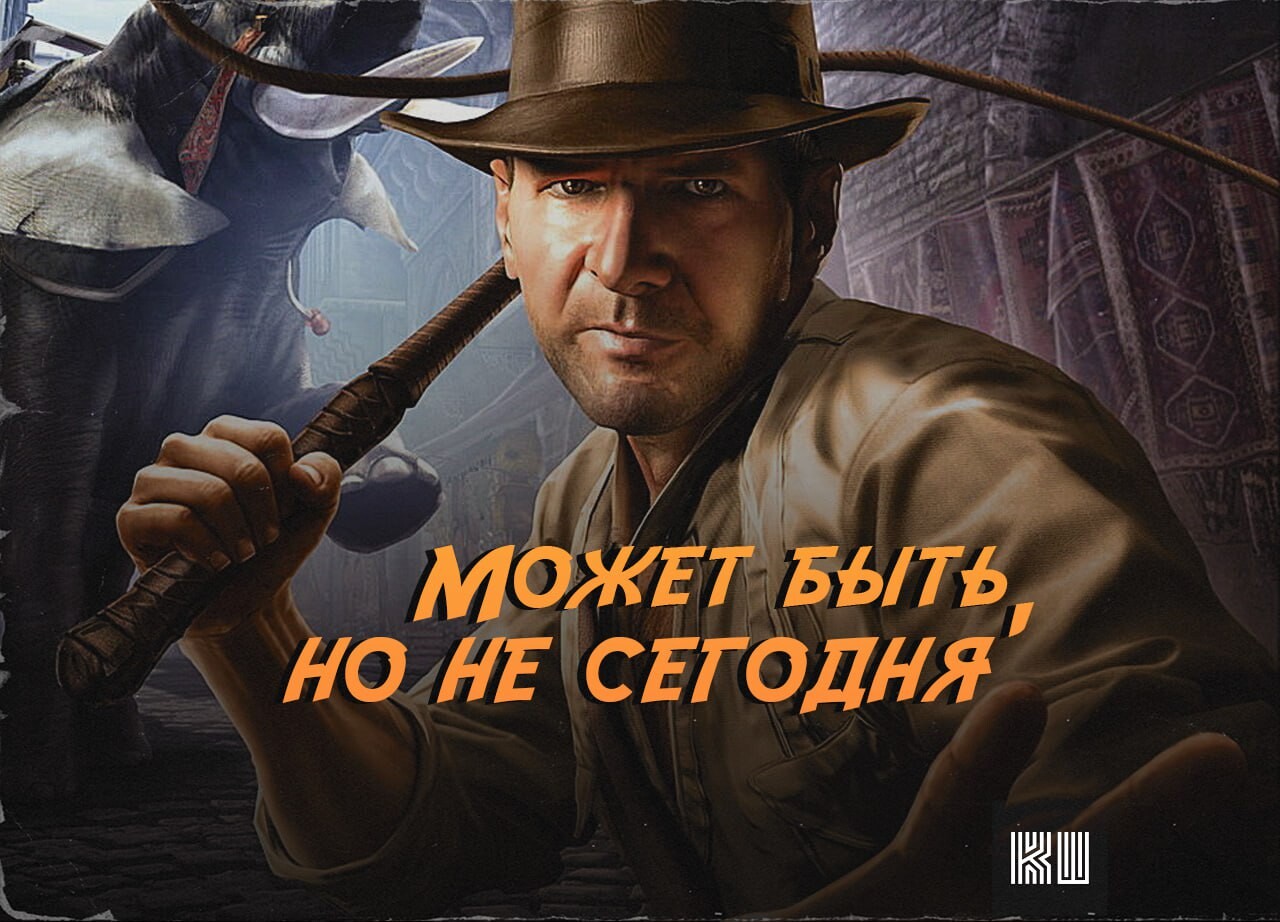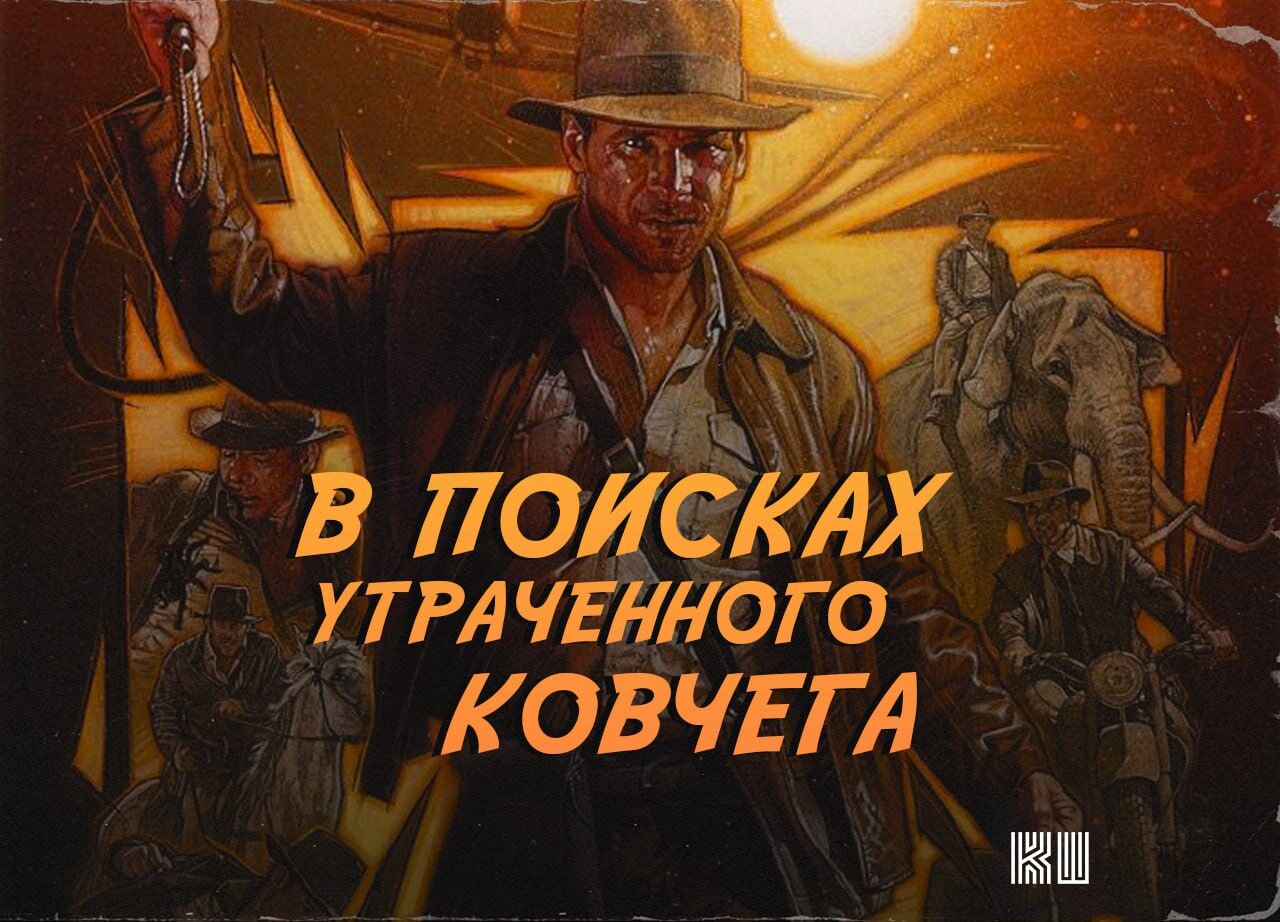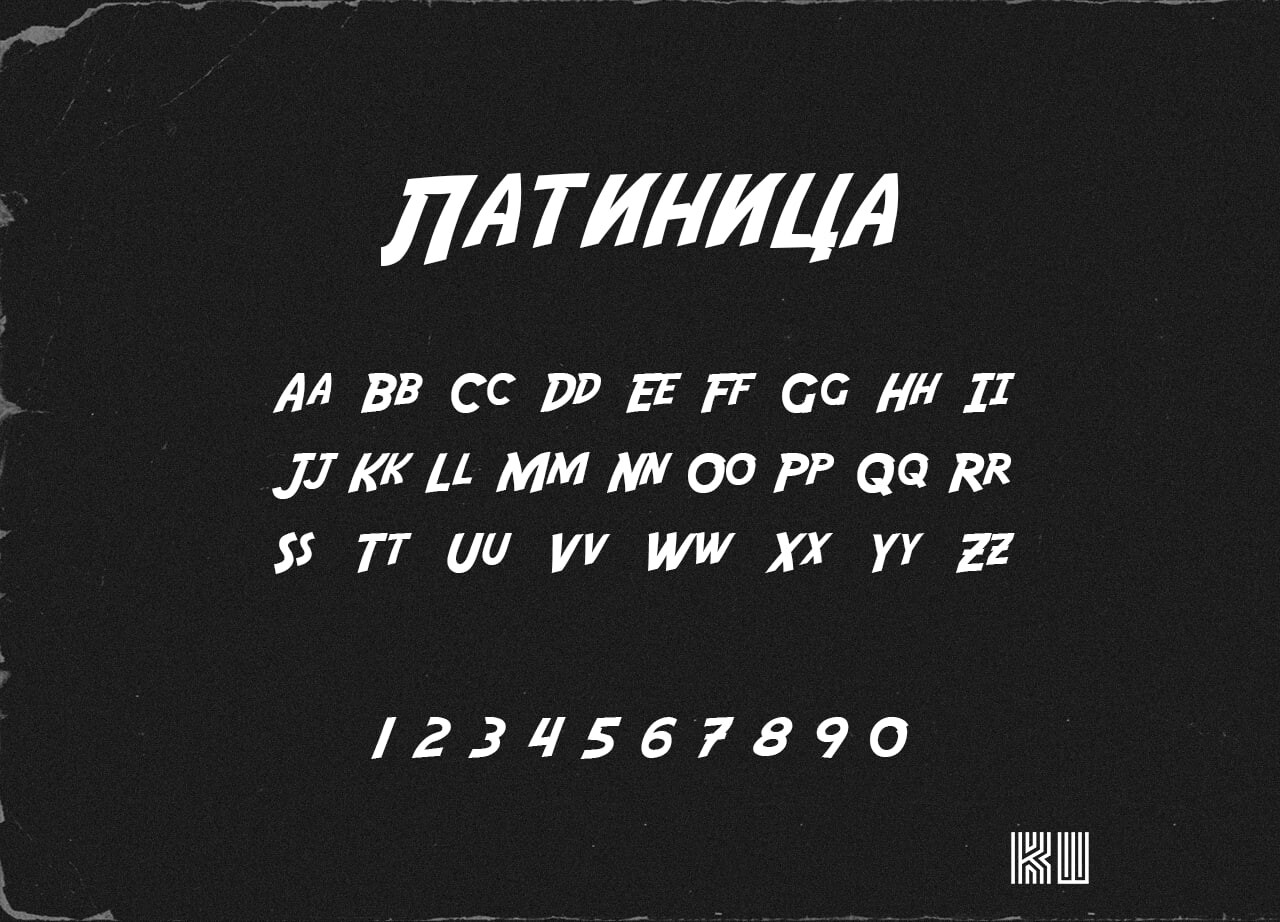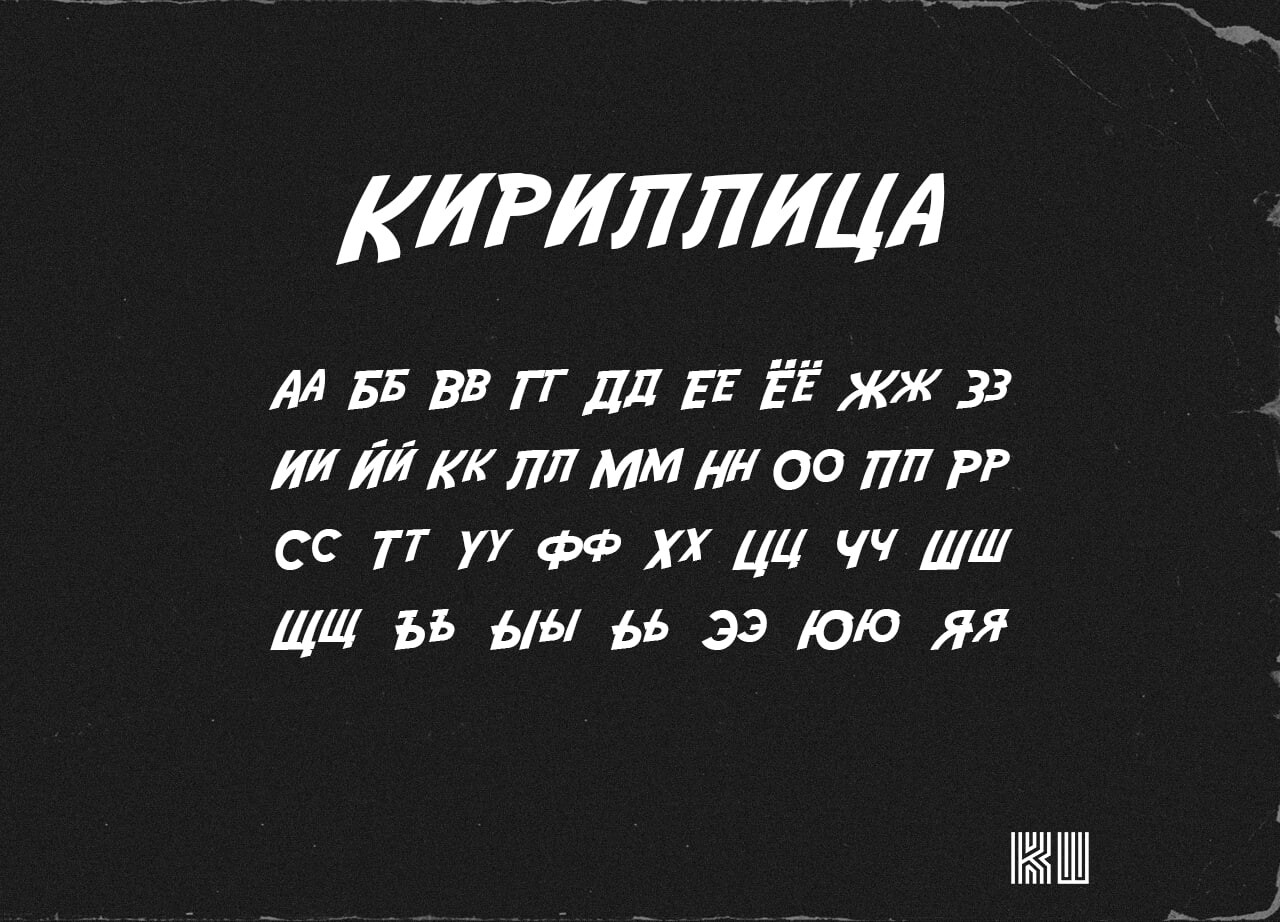
Шрифт "Adventure Indiana Jones": когда надпись сама ищет сокровища 🗺️✨
Ты когда-нибудь замечала, как один шрифт может перенести тебя в джунгли, древние храмы и погоню на тележке? Вот именно так действует "Adventure Indiana Jones" — не просто набор букв, а визуальный портал в мир приключений. Он не просто пишет. Он шепчет: "За мной. Там, за поворотом — артефакт". И да, если ты поставишь его на приглашение на день рождения — гости придут в шляпах и с бичами. 🎩
Не шрифт, а артефакт
Этот тип шрифта — прямая отсылка к легендарным титрам "Индиана Джонс": грубоватые, слегка потрёпанные, будто их вырезали на камне или написали углём в пещере. Каждая буква — как след древнего письма, который только что расшифровал Инди. Он не гладкий. Не идеальный. И в этом — его сила. Потому что приключения — не про безупречность. Они про пыль, риск и немного хаоса.
Где использовать — и где не стоит
Хочешь оформить квест для друзей? Сделать обложку для дневника путешественника? Или просто подписать фото с отпуска в стиле "Я нашла храм, но забыла солнцезащитный крем"? Тогда вперёд! Но не ставь его в резюме. Потому что HR-менеджер может подумать, что ты ищешь не работу, а Золотой идол. 😏
А ведь самое волшебное — что этот шрифт напоминает: мир полон тайн, и иногда достаточно одной надписи, чтобы захотелось выйти за дверь и начать своё приключение. Даже если оно — до ближайшего парка. С бутылкой воды и картой Google.